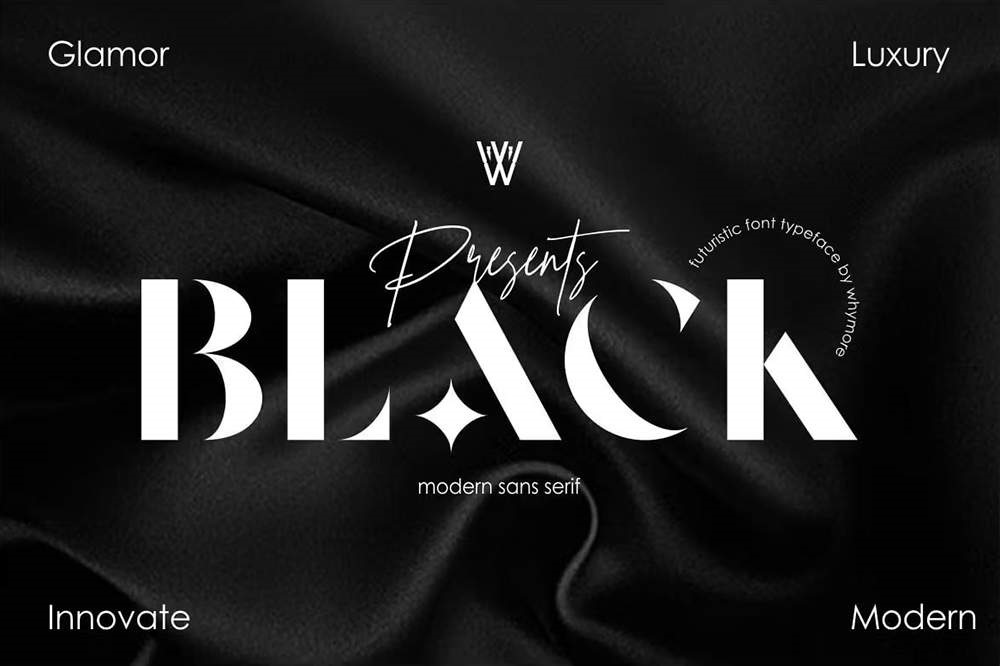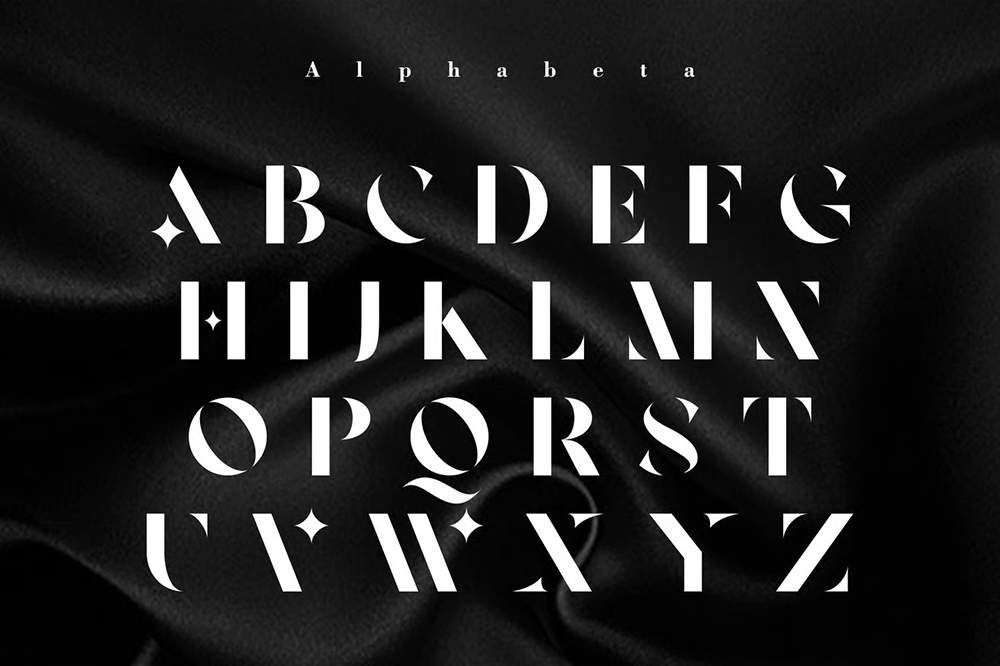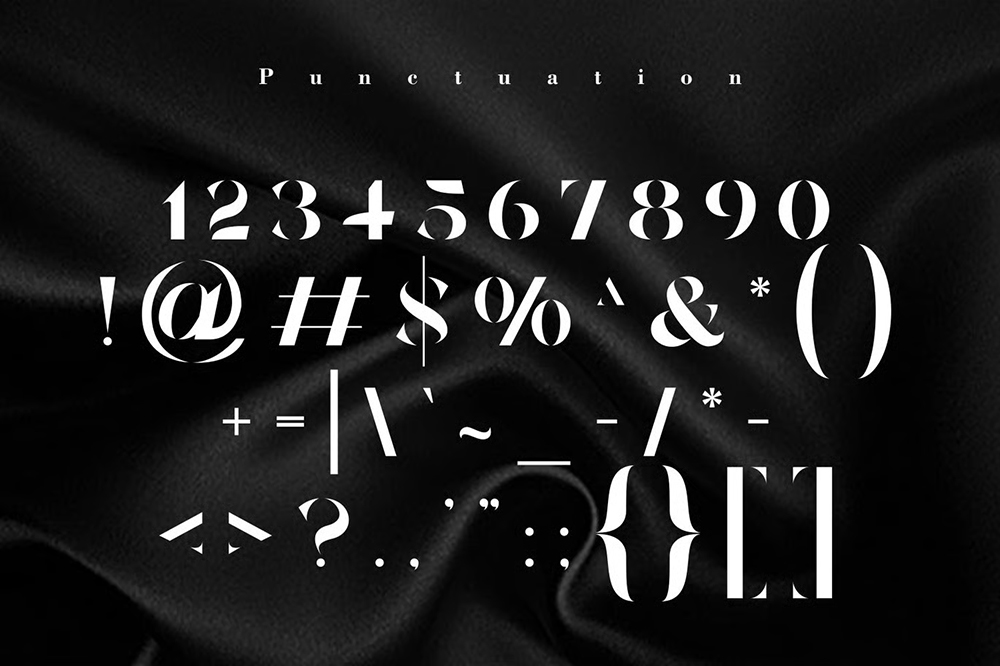
فونت پرمیوم و انگلیسی Black Font حس کنتراست را القا میکند اما همچنان در محدوده معقولی قرار دارد. و از اشکال ضخیم به اشکال نازک با تزئیناتی…
فونت پرمیوم و انگلیسی Black Font حس کنتراست را القا میکند اما همچنان در محدوده معقولی قرار دارد. و از اشکال ضخیم به اشکال نازک با تزئیناتی که کاملاً خلاقانه هستند، به نظر میرسد. سطح ضخامت و نازکی فیلد فونت به گونهای بهرهبرداری کرد و گزینه دیگری در مورد سبک طراحی و دکوراسیون برای نمایش کالاهای خود در بازار به شما ارائه دهد.
مزایای استفاده از فونت لاتین Black چیست؟